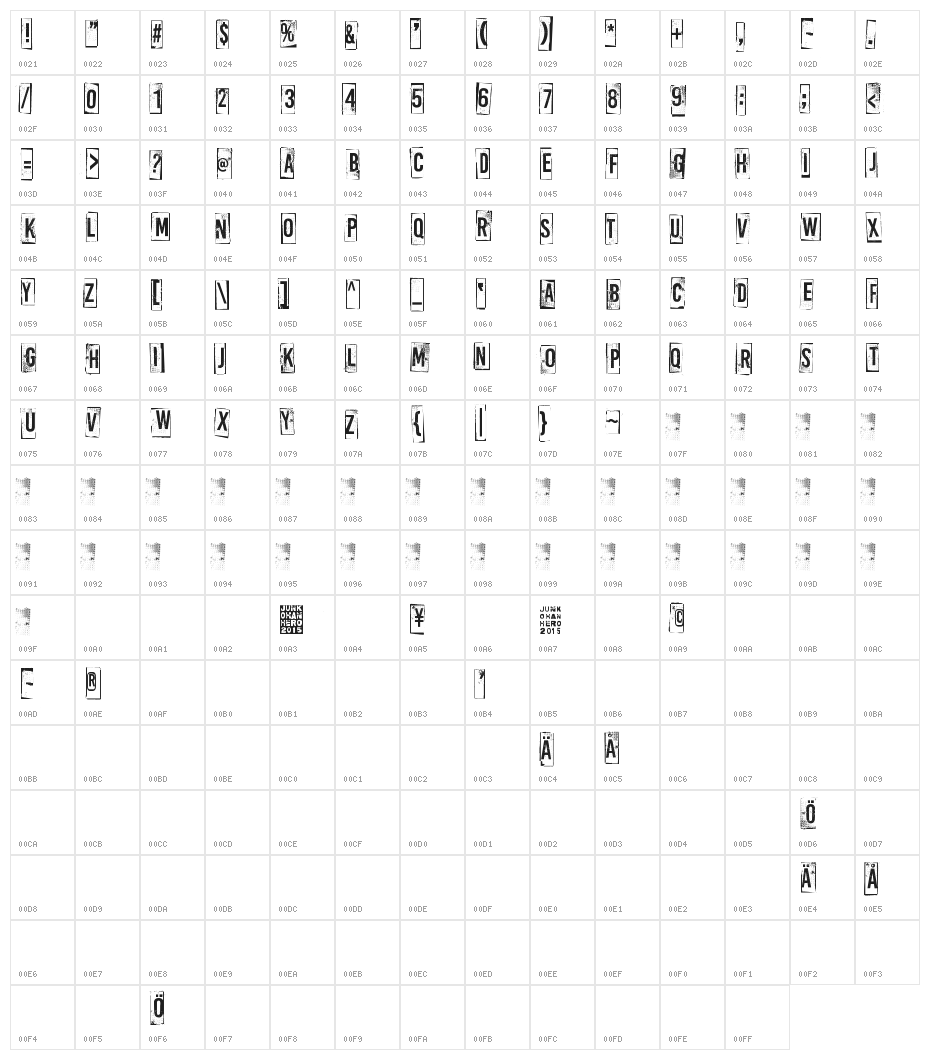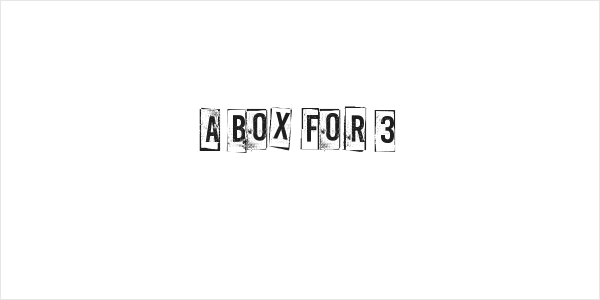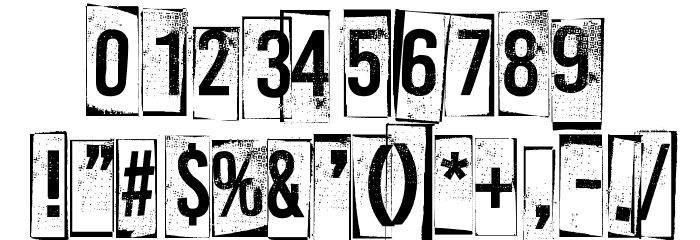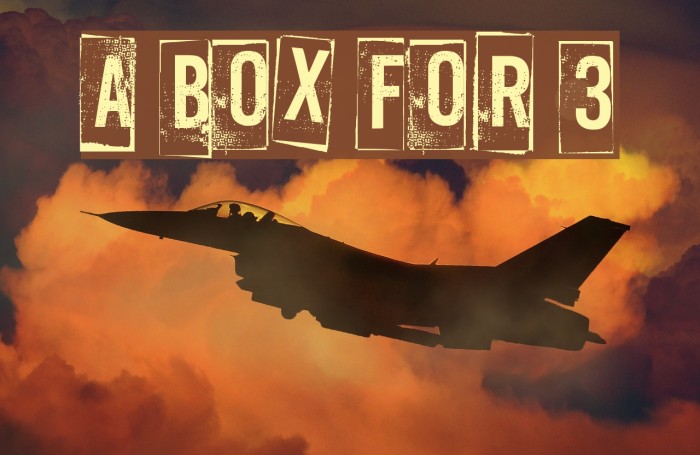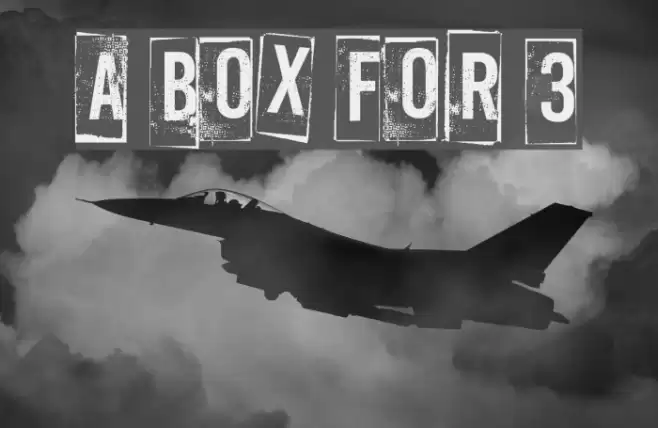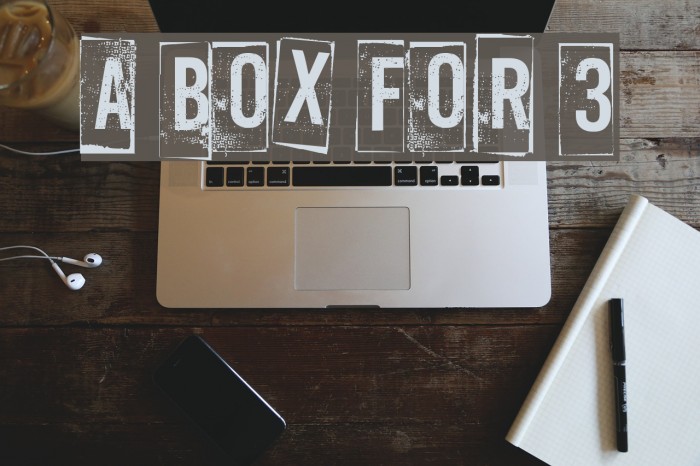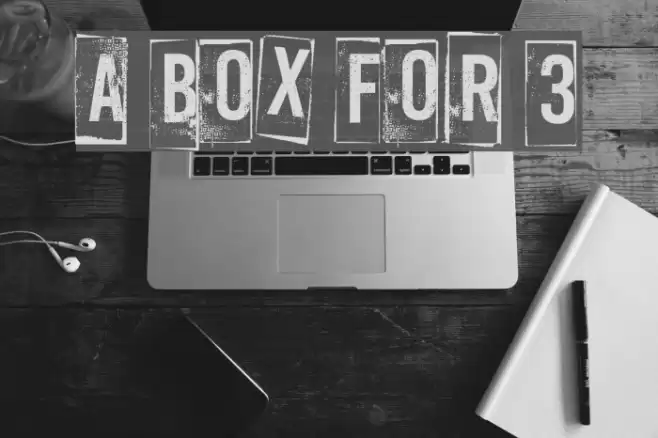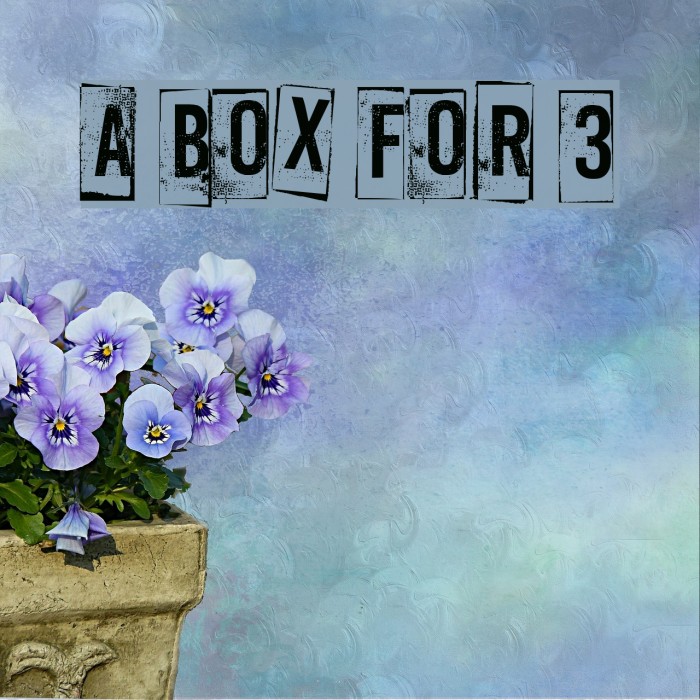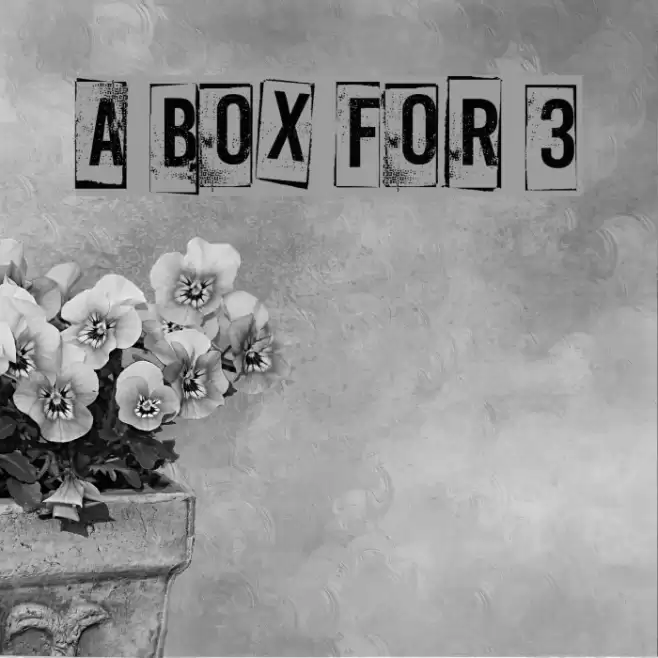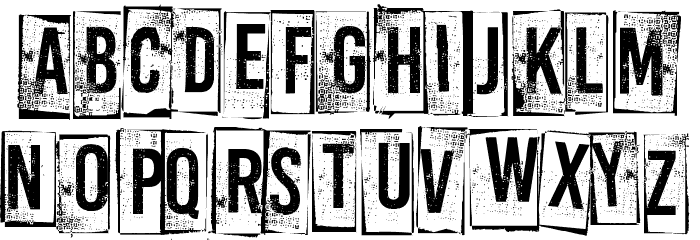
A Box For 3 Font
✎ Distorted Eroded
| Nome | A Box For 3 |
| Categorias | Distorted Eroded |
| Projetos propostos | Ideal for posters, album covers, branding for vintage-themed products, or any design needing a rugged, industrial vibe. |